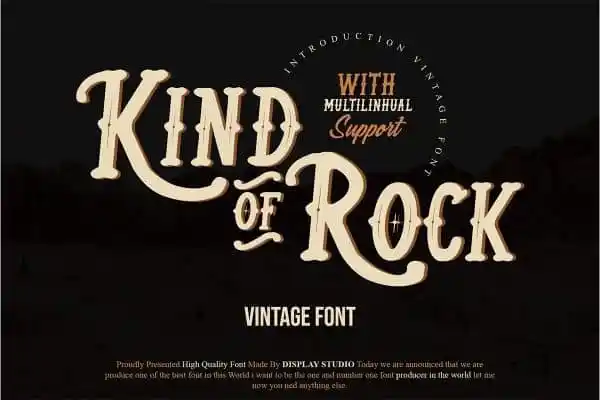
Kind Of Rock Display Font – Download Grátis
A Kind Of Rock Display Font é uma escolha ideal para quem busca uma fonte com estilo moderno para ambientes de design que exigem destaque visual. Inspirada nos tradições da arte manual, esta fonte all-caps foi cuidadosamente criada para destacar textos em mídias digitais e impressões. Com linhas sóbrias e harmoniosas, ela é perfeita para aplicativos de redes sociais, banners de marketing, ou qualquer outro ambiente onde se deseja chamar a atenção com estilo. Seu design cuidadosamente meticuloso evoca uma atmosfera de confiança e sofisticação, projetada para dar um toque de personalidade a qualquer projeto visual. A Kind Of Rock Display Font é uma ótima opção para quem busca uma fonte única que se encaixa perfeitamente em ambientes onde o destaque visual é essencial.